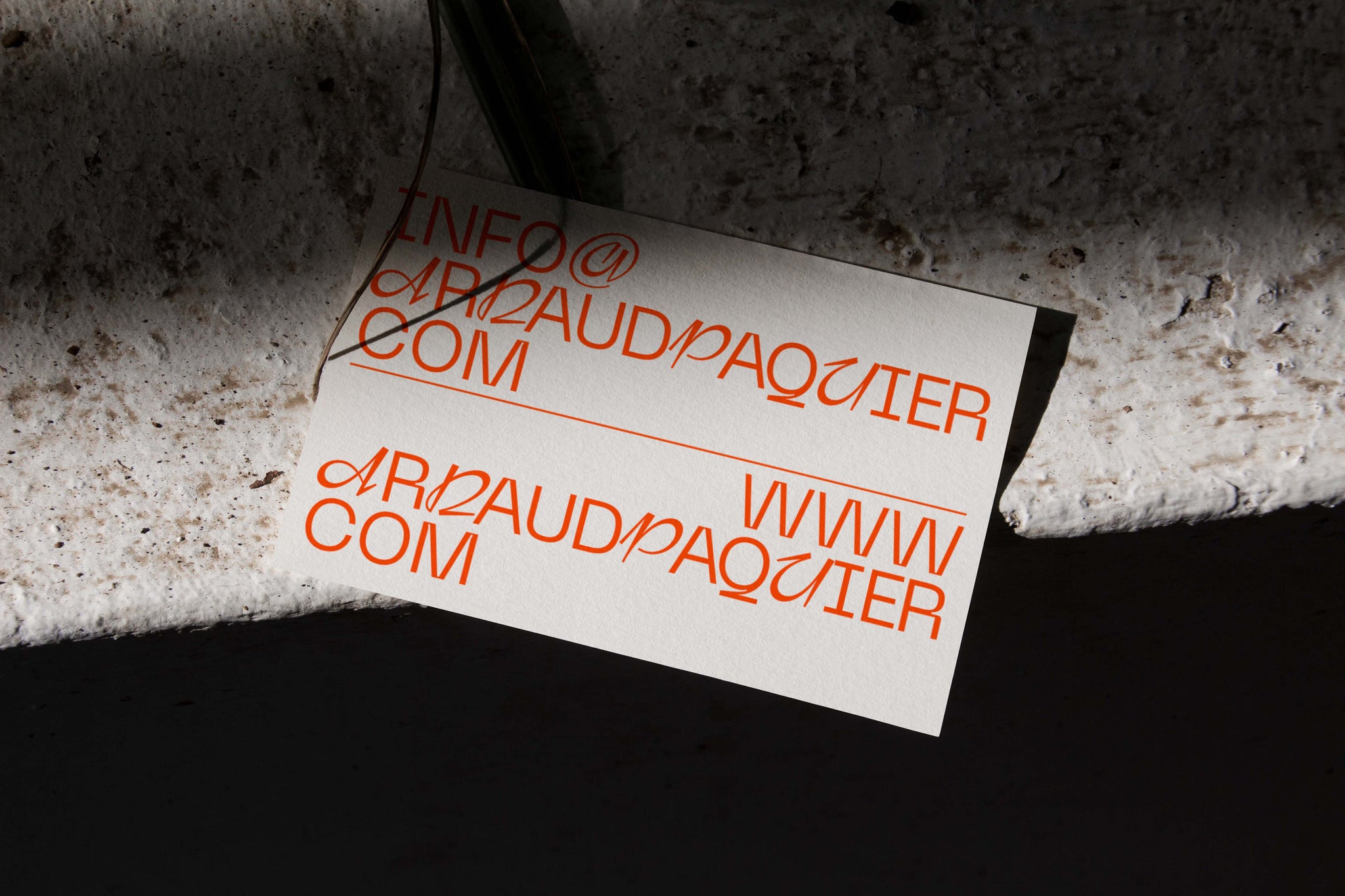
Le premier recueil d'Arnaud Paquier, 1_Rochers, propose un inventaire de paysages de montagne colorés capturés lors de ses voyages.
Couche par couche, il peint, marque et gratte la toile, cachant une histoire unique dans chaque tableau.
La typographie d'affichage utilisée dans l'identité visuelle fait référence à la gestuelle spontanée et libre du peintre. Elle est associée à une typographie géométrique sans empattement inspirée de l'esthétique de la robotique et des machines. Cette confrontation crée un dialogue visuel à la fois vibrant et élégant.
La notion de mouvement est renforcée par l'architecture du site. Des effets de parallaxe révèlent les paysages peints comme des décors en mouvement. Les œuvres peuvent également être découvertes dans un espace virtuel 3D qui présente les peintures de l'artiste sous un jour nouveau.